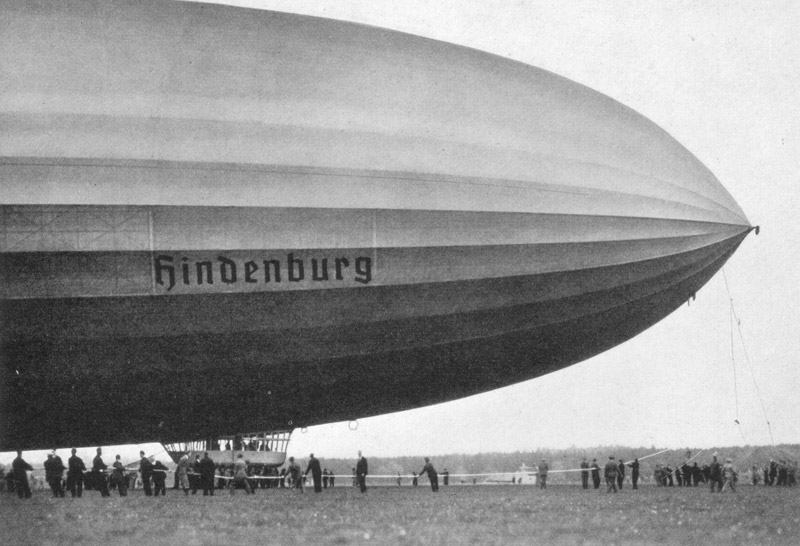
Der Hindenburg-Schriftzug
Mich würde jetzt interessieren, wie man das damals skaliert hat. Da muß es ja eine technische Routine gegeben haben, wie man einen Schriftzug von der Papiervorlage in diese Dimension gebracht hat. Ein gigantischer Storchenschnabel? Ein Rastergitter? Oder war das jenseits aller Routine eine Sache des reinen Augenmaßes? Immerhin scheint der Meister ja den Prozeß zu überwachen.
Deutsche Schrift in der deutschen Luft- und Seefahrt
Von Georg Wagner, Berlin
Als ich mich in den ersten Tagen dieses Jahres vor die Aufgabe gestellt sah, einen Vorschlag für die erstmalige Deutsch-Beschriftung eines Zeppelin-Luftschiffes, und zwar mit dem Namen unseres unvergeßlichen Feldmarschalls und Reichspräsidenten »Hindenburg«, zu entwerfen – um welche Lösung sich der Bund für deutsche Schrift schon jahrelang bemüht hatte –, da war es nur eine leise Hoffnung, die mich an die endgültige Ausführung glauben ließ.
Mancherlei Bedenken um die Zweckmäßigkeit eines Wortes in deutscher Schrift für den Weltverkehr und im besonderen für die Reisen des neuen Zeppelin-Luftschiffs L. Z. 129 nach Latein-Amerika waren trotz heutiger, gegen frühere Zeiten grundlegend gewandelten Anschauung über den Kulturwert deutscher Schriftgestaltung noch lebendig, und es galt als selbstverständliches Erfordernis, daß dieses Wortzeichen »Hindenburg« ohne jede Schwierigkeit und überall zu lesen sein mußte.
Dieselben Bedenken gegen die Deutsch-Beschriftung hatte auch die Leitung unserer Kriegsflotte, und es waren viele Schwierigkeiten zu überwinden, bis unsere Matrosen schon durch ihre Mützenbänder in deutscher Schrift ihre Heimat deutlich erkennen ließen. Heute tragen unsere sämtlichen Kriegsschiffe und die Schiffe des Seedienstes Ostpreußen stolz und selbstverständlich am Heck ihre Namen, die uns allen Symbole für Vaterlandsliebe und Pflichterfüllung bedeuten sollen, in deutscher Schrift. Unsere Handelsflotte läßt zur Zeit, wenn auch sicher nicht mehr lange, mit dem gleichen Entschluß noch etwas auf sich warten.
Aus der mir übergebenen Werkzeichnung entnahm ich, daß mir für den Luftschiffnamen eine Fläche von 15 m Länge und einer mittleren Höhe von 2,75 m zur Verfügung stand.
Nach reiflicher Überlegung, und nachdem ich den Namenszug in vielen historischen Formen geschrieben und auch aufgezeichnet hatte, kam ich zu den Ergebnis, daß für diesen Zweck nur eine dem heutigen Stilempfinden werkgerecht geschriebene Schriftformung in Frage kommen konnte, und nach der Erfahrung, daß, im Gegensatz zu dem gewohnten enggestellten Wortbild, für die Fernbesichtigung nur die durch größere Abstände gesperrte Buchstabenstellung anzuwenden ist. Diese fachmännischen Erwägungen wurden von sämtlichen für die Genehmigung zuständigen Amtsstellen gebilligt und ich erhielt kurz vor dem ersten Auslaufen des Luftschiffes, den Auftrag, die genehmigte Beschriftung des Zeppelin-Riesen selbst in Friedrichshafen vorzunehmen. Auf dem Boden der Werkhalle, unter dem Luftschiffkörper, dessen gewaltige Ausmaße zuerst erdrückend auf mich wirkten, wurde nun das Wort »Hindenburg« in der erforderlichen Größe auf eine über den Boden gebreitete silberfarbene Cellon-Aluminium-Stoffbahn aufgemalt und dann zur Prüfung der optischen Wirkung ungefähr 18 m hoch an der Innenseite der fahrbaren, annähernd 50 m hohen Hallentür aufgehängt. Da das Ergebnis mich nicht ganz zufriedenstellte, wurde eine neue Stoffbahn mit dem Namenszug unter Berücksichtigung der als notwendig erkannten Änderungen bemalt und schließlich das Resultat dieser eingehenden Vorarbeiten in den Zeichnungen für die einzelnen Buchstaben festgelegt.
Von der Hallendecke herabhängende Schwebegerüste gaben den Malern den erforderlichen Halt, um das Aufpausen der einzelnen Buchstaben und das Ausmalen derselben am Schiffskörper vorzunehmen. Hierzu wurde zinnoberrote Farbe bestimmt, die erfahrungsgemäß das beste Fern-Erkennen ermöglicht.
Seine ersten Fahrten hat der Zeppelin »Hindenburg« unter der Begeisterung unserer deutschen Volksgenossen, im überflogenen Auslande aufrichtig bewundert, inzwischen glücklich und erfolgreich beendet. Niemand hat Anstoß an dem deutschriftigen Namenszug genommen, auch niemand in den besuchten Fremdländern, aber alle unsere Volksgenossen in Deutschland und gewiß noch viel eindringlicher unserer deutschen Brüder im Auslande werden in aufrichtiger Freude empfinden, daß neben deutscher Sprache auch deutsche Schrift Weltgeltung verdient und dank unserem Führer auch für immer behalten wird. Wir wollen hoffen, daß dieses Beispiel richtunggebend alle Möglichkeiten der Werbung für deutsches Kulturgut beeinflussen wird.
Zinnoberrote Schrift - interessant! Wird soweit ich es kenne immer schwarz dargestellt.
Exakt! Wenn man nach Bildern im www sucht, findet man allerdings auch den Schriftzug in rot Farbe in Darstellungen der HINDENBURG.
Eine Frage zu den Bildern und der wahrscheinlichen Arbeitsweise:
Der Testbanner in Originalgröße mit HINDENBURG war vermutlich in der zinnoberroten Farbe um die Wirkung in der Gesamtheit einzuschätzen. Sind die kleineren Muster in Zinnoberrot oder Schwarz angelegt? Wir würdet ihr vorgehen?
Das wird einfach eine Frage sein, in welcher Farbe die Namen der Vorgängermodelle waren. Wenn ich vor hätte rot zu nutzen, würde ich auch die kleinen Entwürfe in dieser Farbe anlegen.